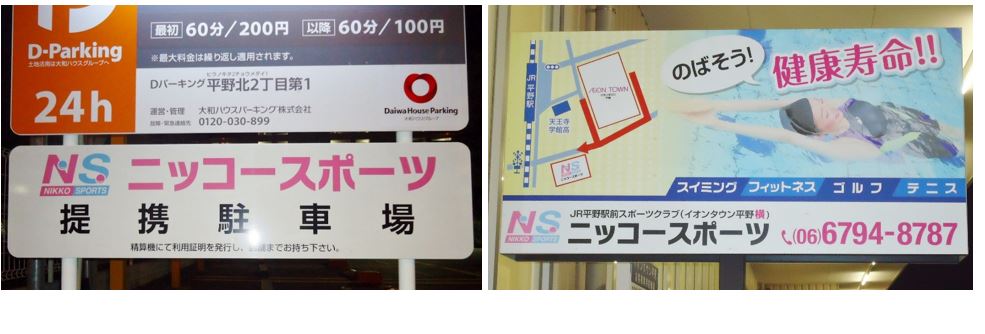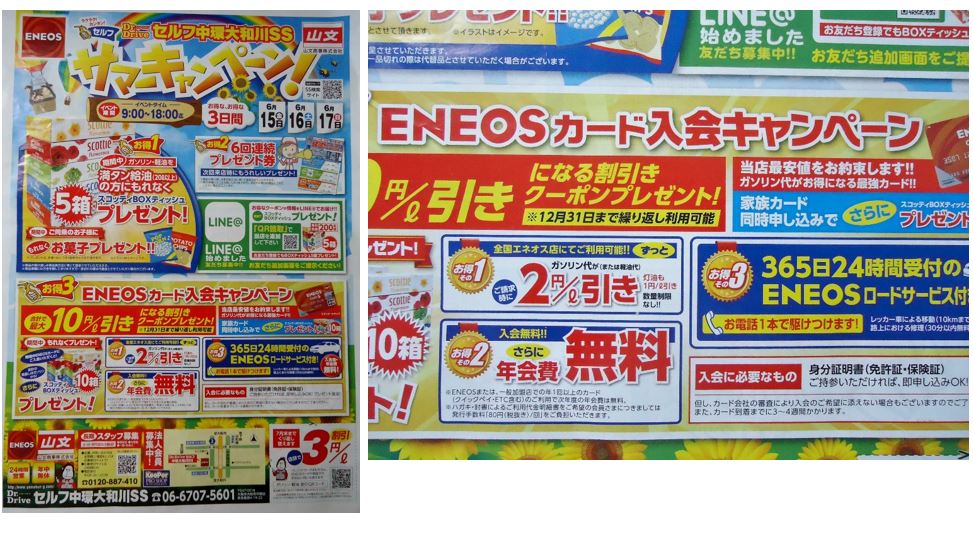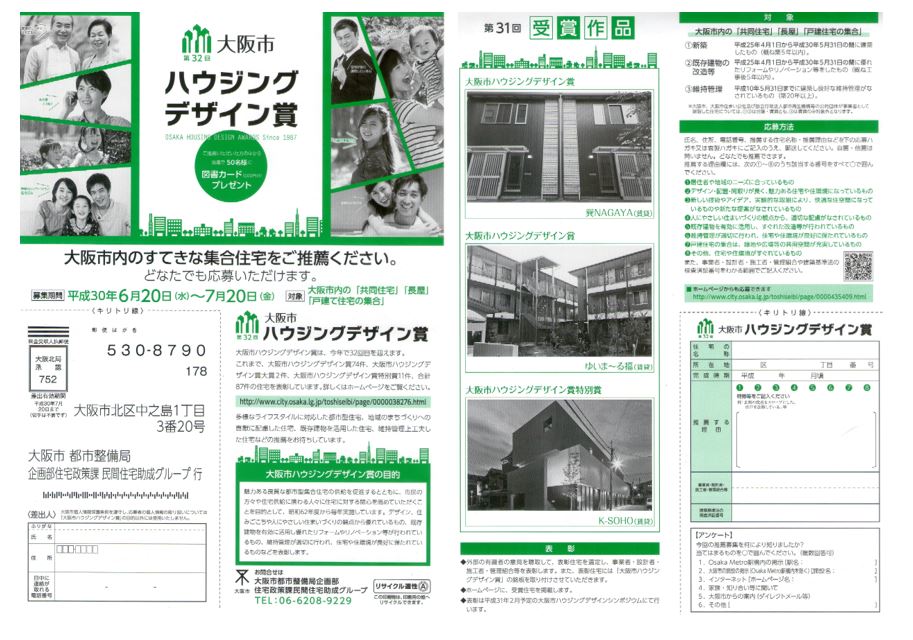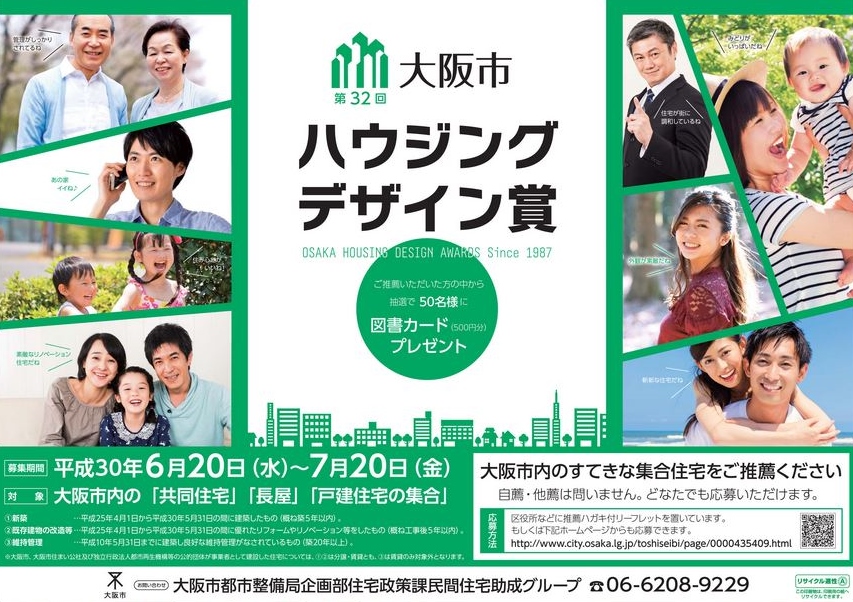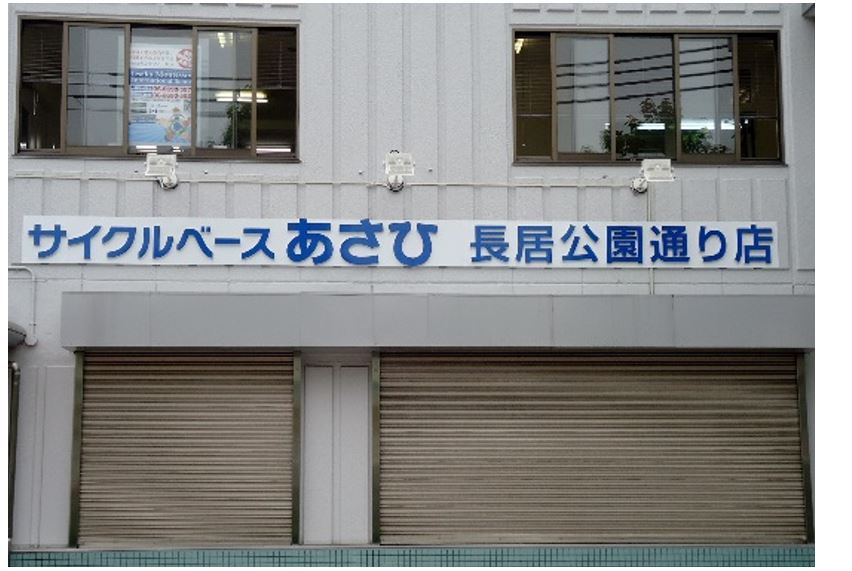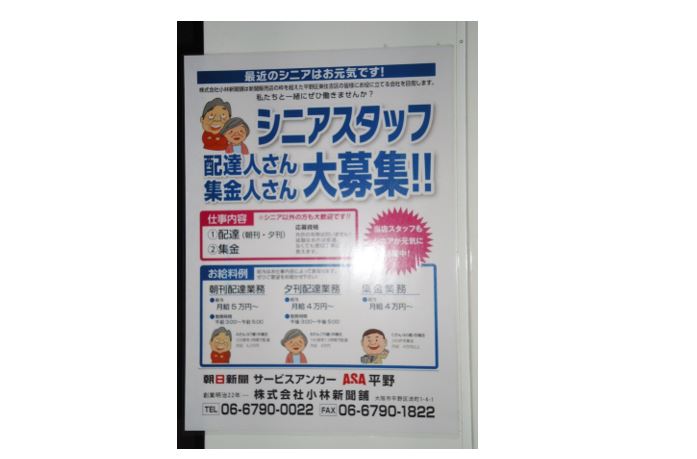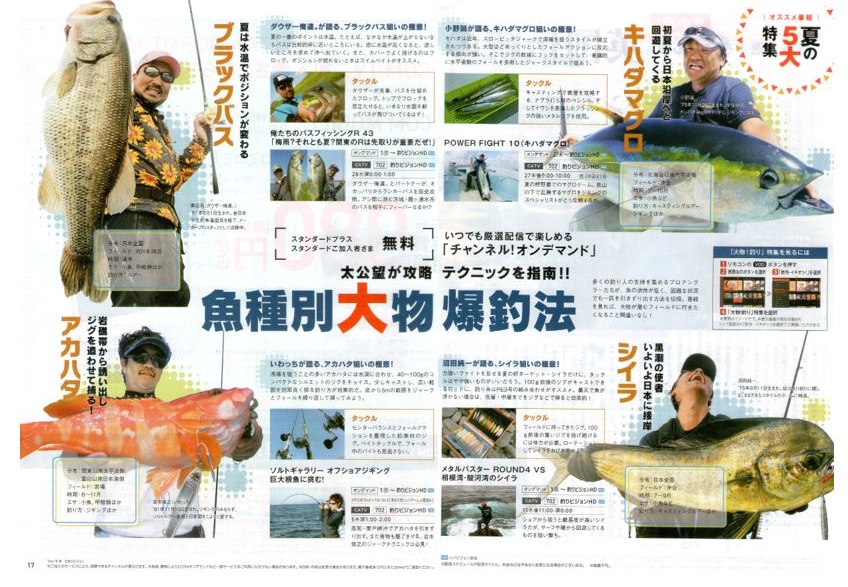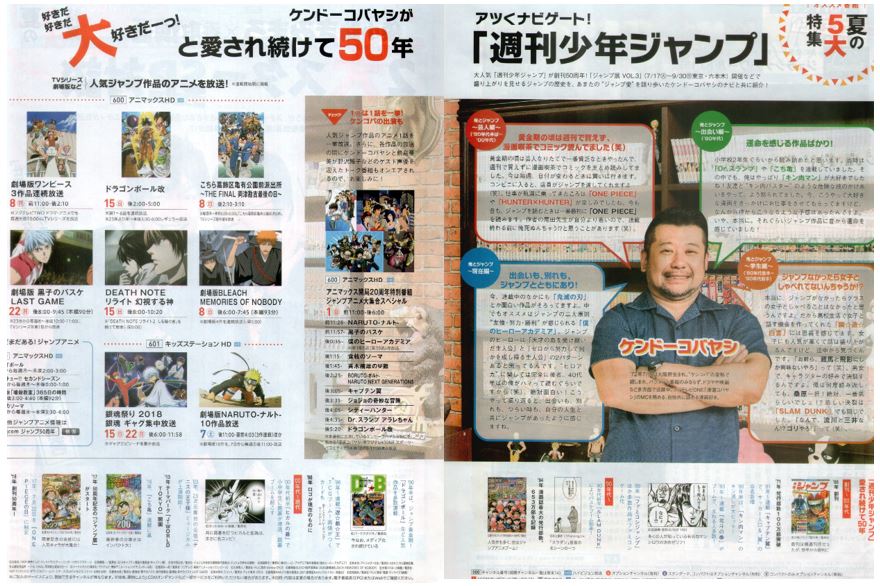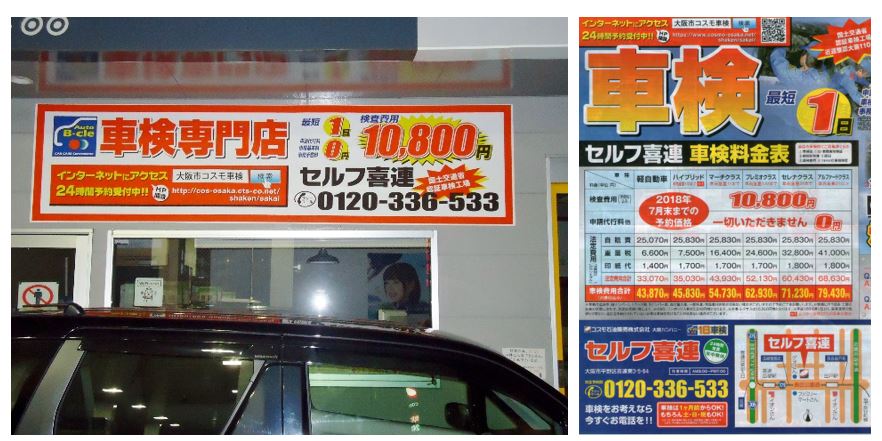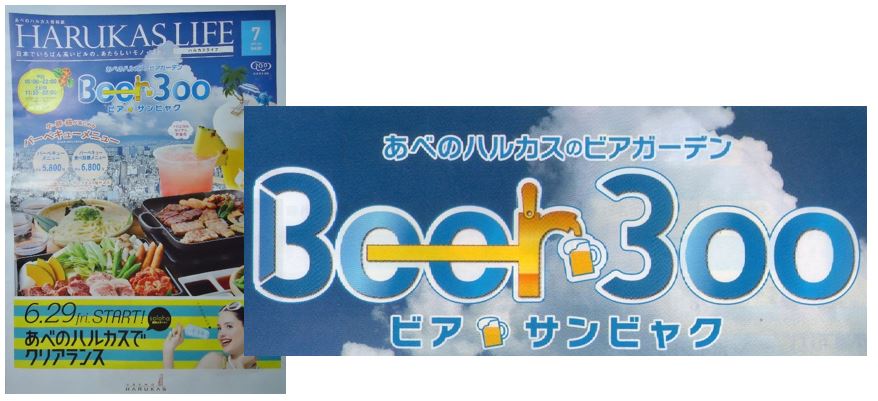
佐藤さん、こんばんは。
12月7日に発売されたNintendo Switch用ソフト『大乱闘スマッシュブラザーズ SPECIAL』のゲーム内でニタラゴ(ロダンNTLG)が使われているようです。
参考にもう1枚。
購読している新聞のおまけで貰える、Y家庭版という本の付録。
中身ページのタイトルにも多用されていた。
大阪府八尾市、ビジネスチャンス発掘フェア主催。展示商談会などのフェア開催案内のハガキです。ロゴタイトルで使われています。
ミニコミ紙「演歌歌謡通信」の見出し&記事です。
これまで「ニタラゴルイカ」は一番太いウェイトとしてきましたが、今回初めて細めの「ニタラゴルイカ」05を使いました。
こんな細いのもすごくいいですね!!
袖見出しの「セプテンバーN」も初めての使用。本文はMです。
こんなコンビーフ、あるんだな…。
今日、SS書籍売り場で見つけました。幼児向け雑誌でニタラゴが大きく使用されています。
小学館「めばえ12月号知育増刊クリスマスひらがなえいごブック」で検索してみてください。小学館のサイトは画面が小さすぎます。通販サイトに良いものがあります。
これですよね。
それにしても派手なゴチャゴチャした表紙だ…。
マクドナルドのCM。
大阪市など、関西2府4県に展開しているカラオケ店の地域配布のチラシです。
ライセンスもののかな書体です。
11月18日に、大阪市浪速区でおこなわれるイベント「ナニワふれあいスタンプラリー」(浪速区体育厚生協会、浪速区役所など主催)のパンフレットです。
ロゴの「ナニワスタンプラリー」です。
今月の9日に公開される「アンクルドリュー」。